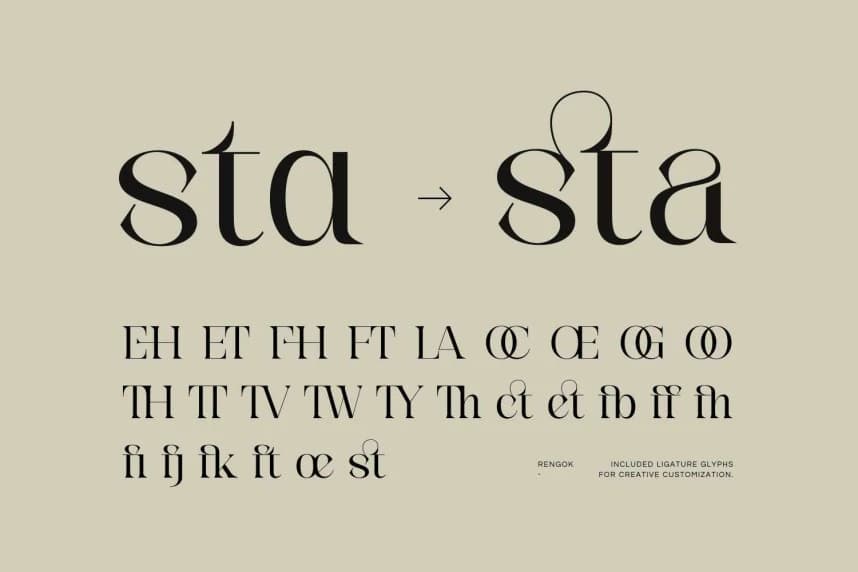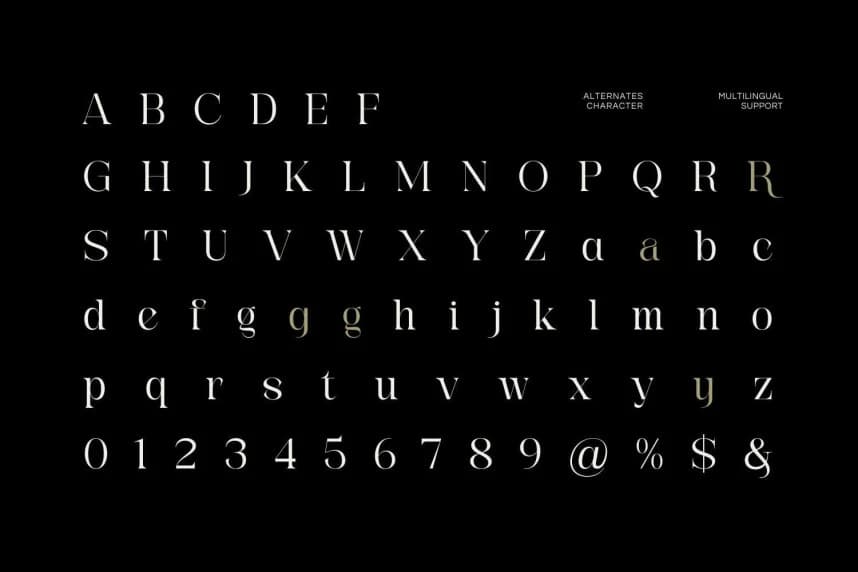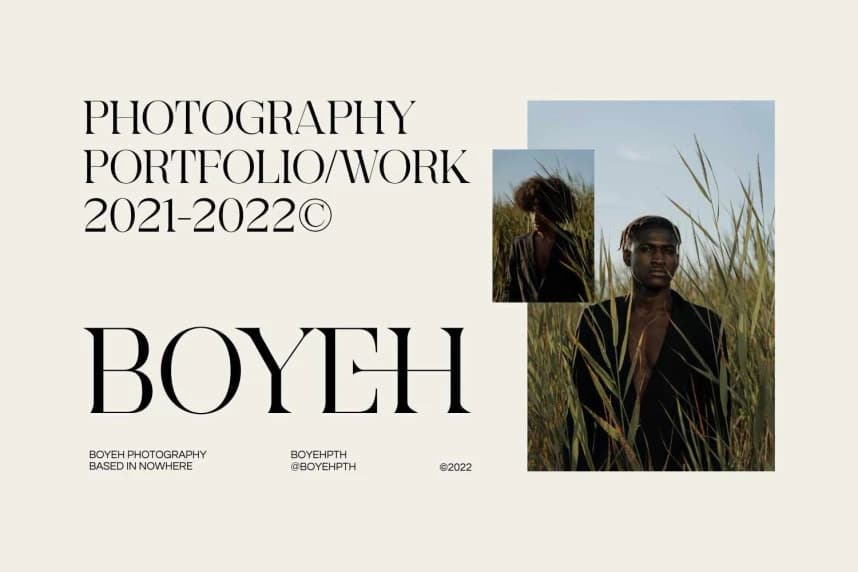
Rengok Font
Rengok Font, sofistike ve zarif bir serif stiline sahip, estetik bir gösterim yazı tipidir ve kalın ile ince çizgiler arasındaki yüksek kontrastla öne çıkar. Klasik bir görünümün yanı sıra çağdaş bir havaya sahip olan bu yazı tipi, keskin serifler ve zarif, uzatılmış harf hatlarıyla karakterizedir.
Rengok Font, kalın ve ince çizgiler arasındaki yüksek kontrasta sahip sofistike ve zarif bir serif stiline sahip, rafine bir estetik gösterim yazı tipidir. Klasik fakat çağdaş bir görünüme sahiptir ve keskin seriflerle zarif, uzun harf biçimleriyle karakterize edilir.